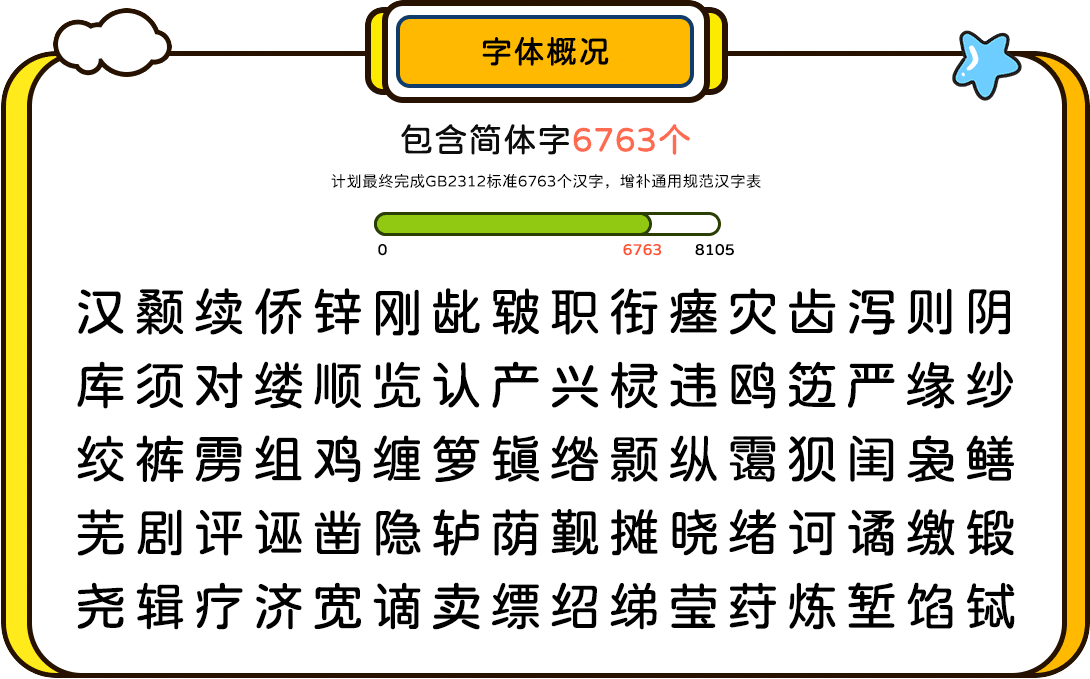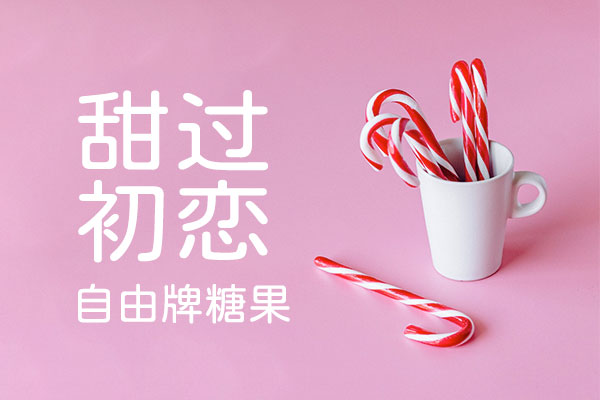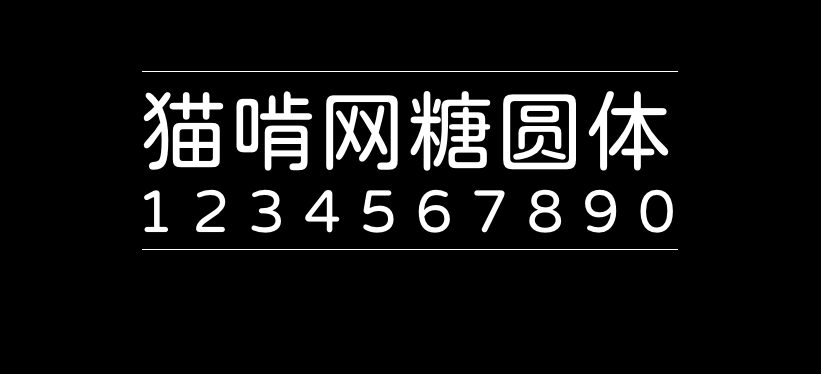
猫啃网糖圆体
猫啃网糖圆体(maoken tangyuan beta 、部分软件中显示为:쎨뿐췸쳇풲쳥)是猫啃网在免费开源的小杉圆体、jf open粉圆的基础上进行整合和增补简体字形而形成的一款字体。
目前猫啃网糖圆体已完成简体GB2312标准6763个汉字,未来继续增补通用规范汉字表。日常使用基本不存在缺字现象。